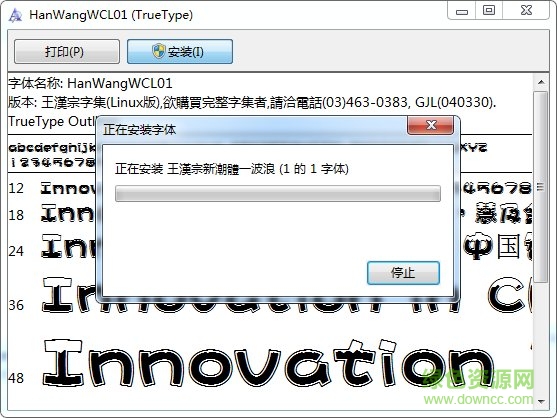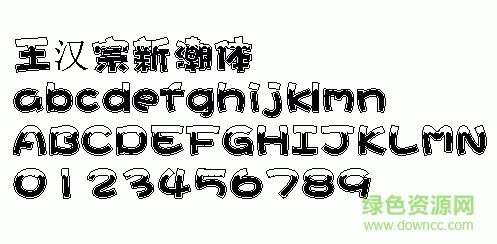
王漢宗新潮字體是王漢宗字體庫推出的一款免費個性字體!這款字體屬于空洞風(fēng)格,主要用途就是用于平面設(shè)計、制作海報等。喜歡的網(wǎng)友可以來綠色資源網(wǎng)下載安裝。
王漢宗新潮體線條結(jié)構(gòu)大方合理,筆鋒犀利,整體效果出色,可以適用于廣告設(shè)計、平面設(shè)計、標(biāo)題正文、書法繪畫等領(lǐng)域!